Привет, друзья! Что-то давно я не делилась свежими подборками красивых шрифтов. Исправляюсь. Сегодня предлагаю вашему вниманию подборочку новых замечательных рукописных шрифтов, причем абсолютно бесплатных. Налетай! :)
1. Jasmine
2. Mark My Words
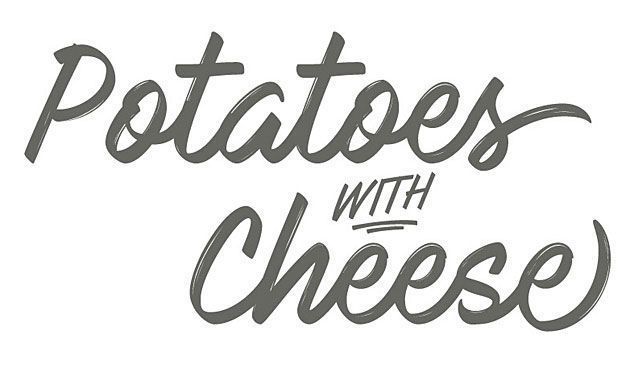
3. Beyond The Mountains
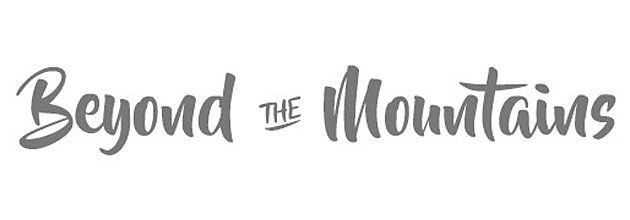
4. Marguerite
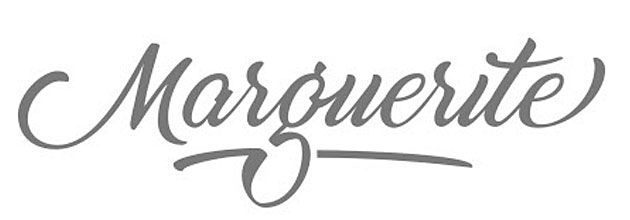
5. Magnolia Sky
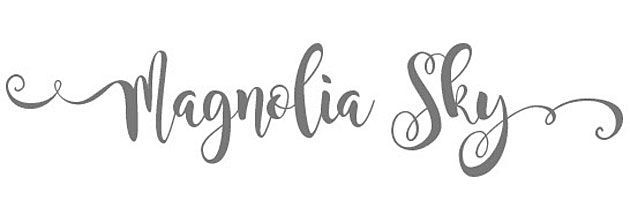
6. Wasted
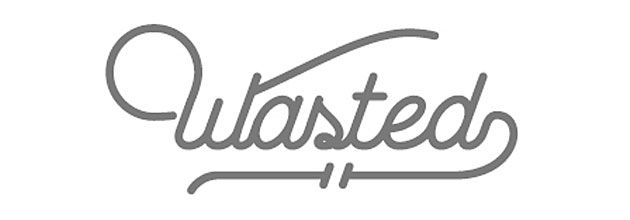
7. Kadisoka
8. Nairobi